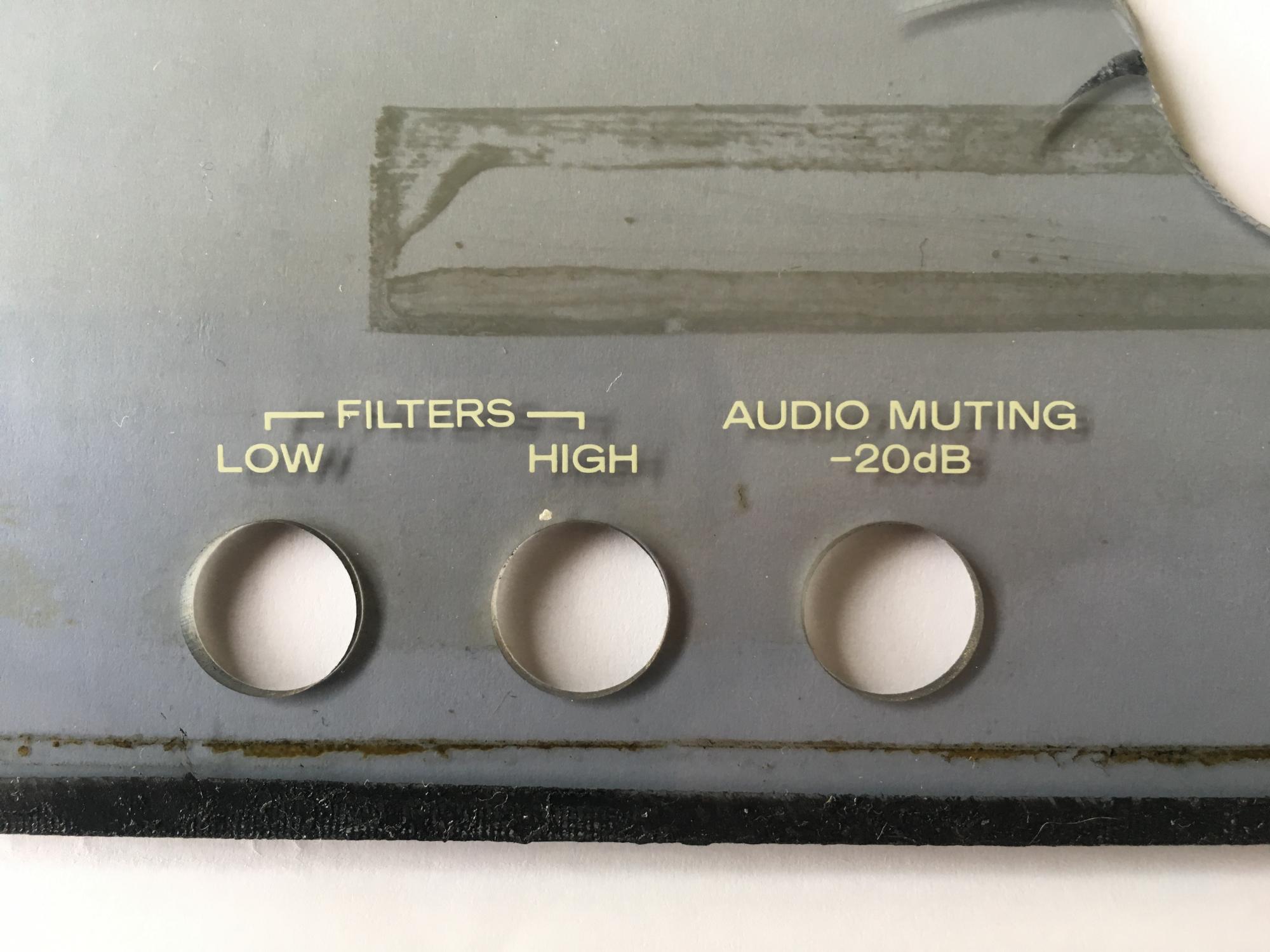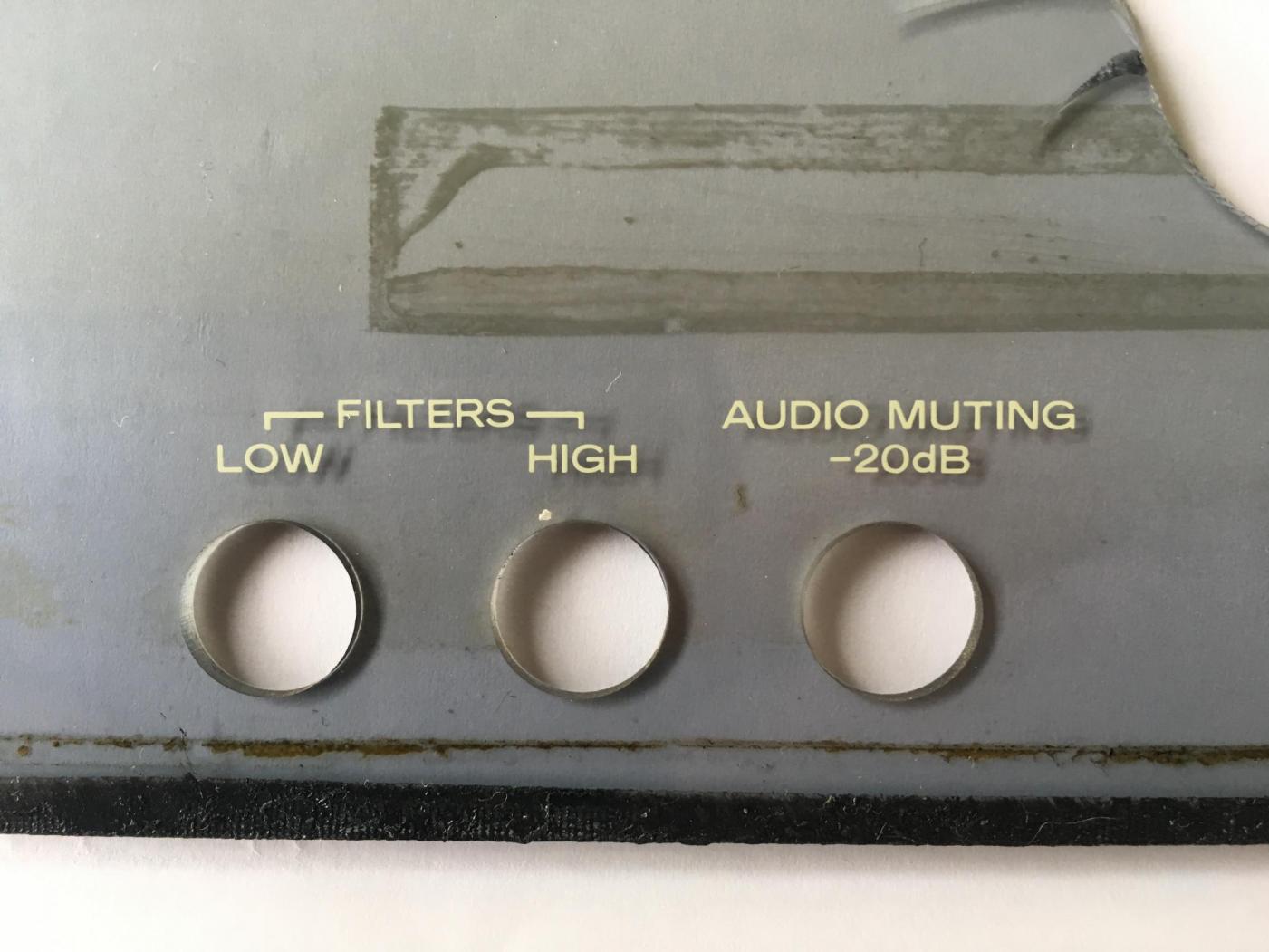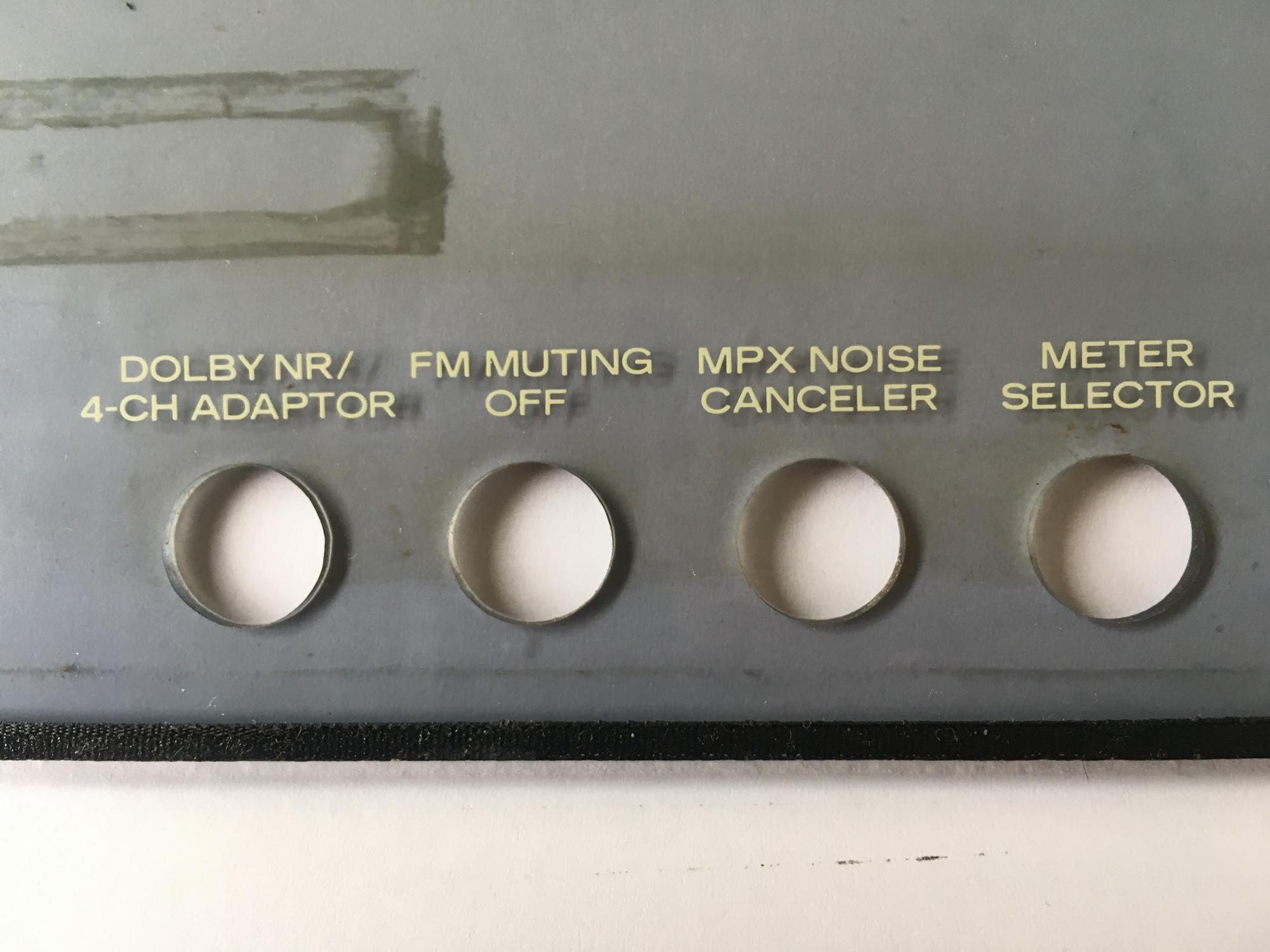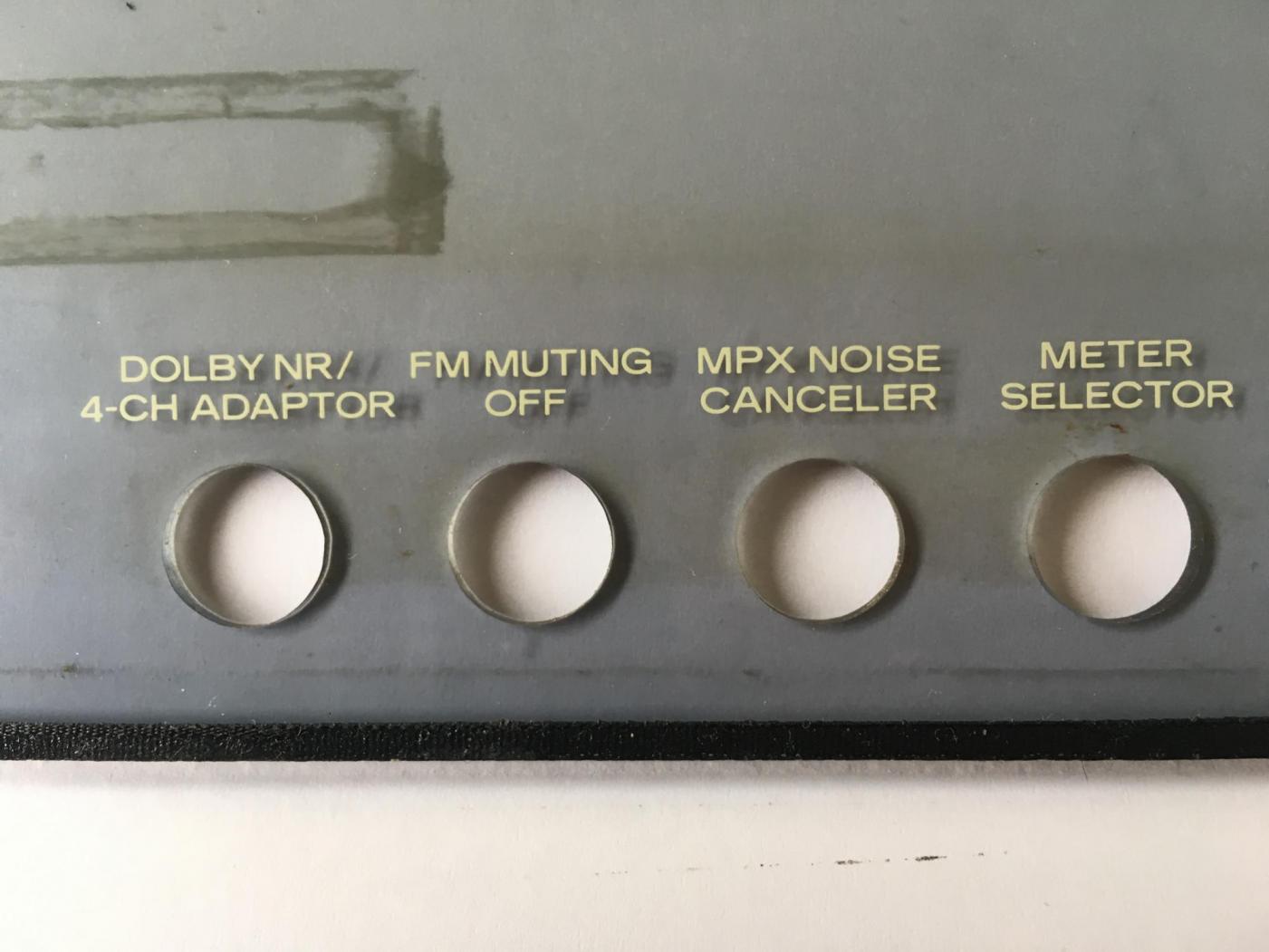
Such Schrift auf altem Sansui-Verstärker
Hallo @Markoff, mit einer Akzidenz Grotesk Regular Extended wärest du hier auf einem guten Weg. Die Formen entsprechen denen in deinen Fotos (bis hin zur kopflastigen /2), die (Eck-)Details nicht immer – was aber an der Drucktechnik und der offenbar sehr geringen Größe der Buchstaben liegen dürfte.